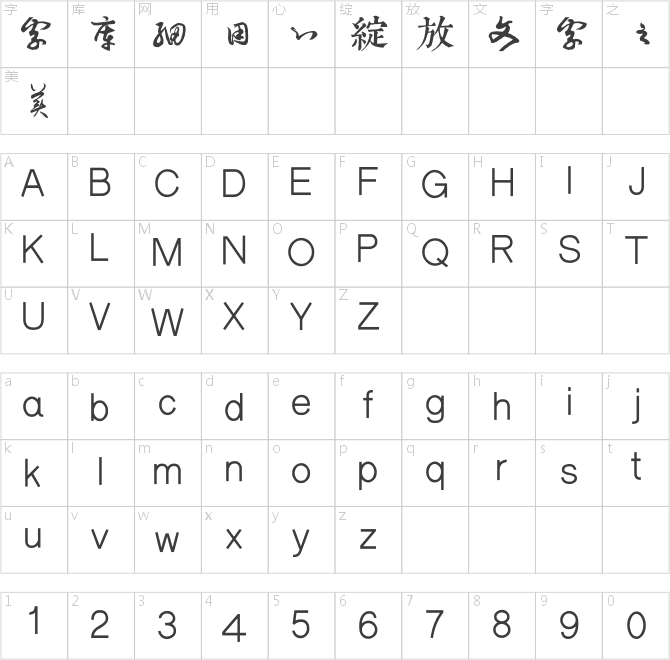
草書
邯鄲
韓紹杰
邯鄲班惟志草書千字文字體下載邯鄲(元)班惟志草書千字文
班惟志,元(約公元一三三o年前后在世)字彥功(一作彥恭),號恕齋,大梁(今河南開封)人,著名詩人、書法家。
邯鄲班惟志草書千字文字體邯鄲(元)班惟志草書千字文字庫是一款讓人賞心悅目、百看不厭的中文字體,適合各類廣告和產(chǎn)品包裝設(shè)計應(yīng)用,字體大小6.51MB,格式為ttf字體,上傳用戶是邯鄲字庫,作者/版權(quán)方為韓紹杰